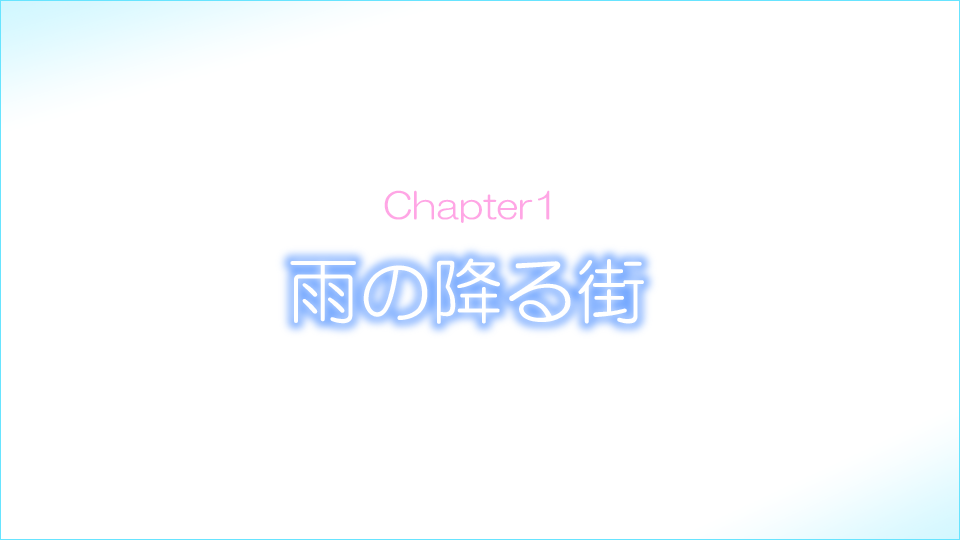
HG丸ゴシックM-PRO フォントの作例
HG丸ゴシックM-PRO フォントの作例です。
モダンな字体の日本語フォントです。視認性も良いです。
HG丸ゴシックM-PRO フォントの作例:画像1
モダンで柔らかみのある字体です。癖がなく使いやすいフォントです。
HG丸ゴシックM-PRO フォントの作例:画像2
フォントに太さがないため、見出しなどでは若干目立ちにくさもありますが、フォントサイズを大きくしたり効果を付けることで、タイトルや見出しでも利用できます。